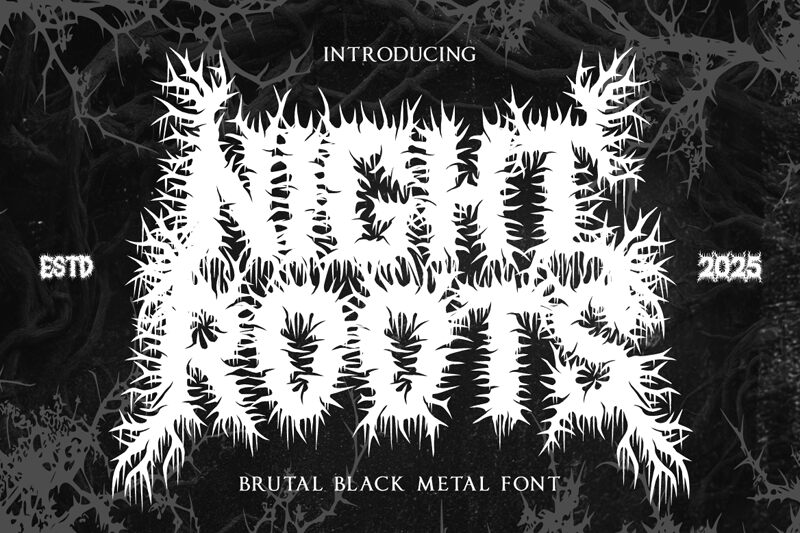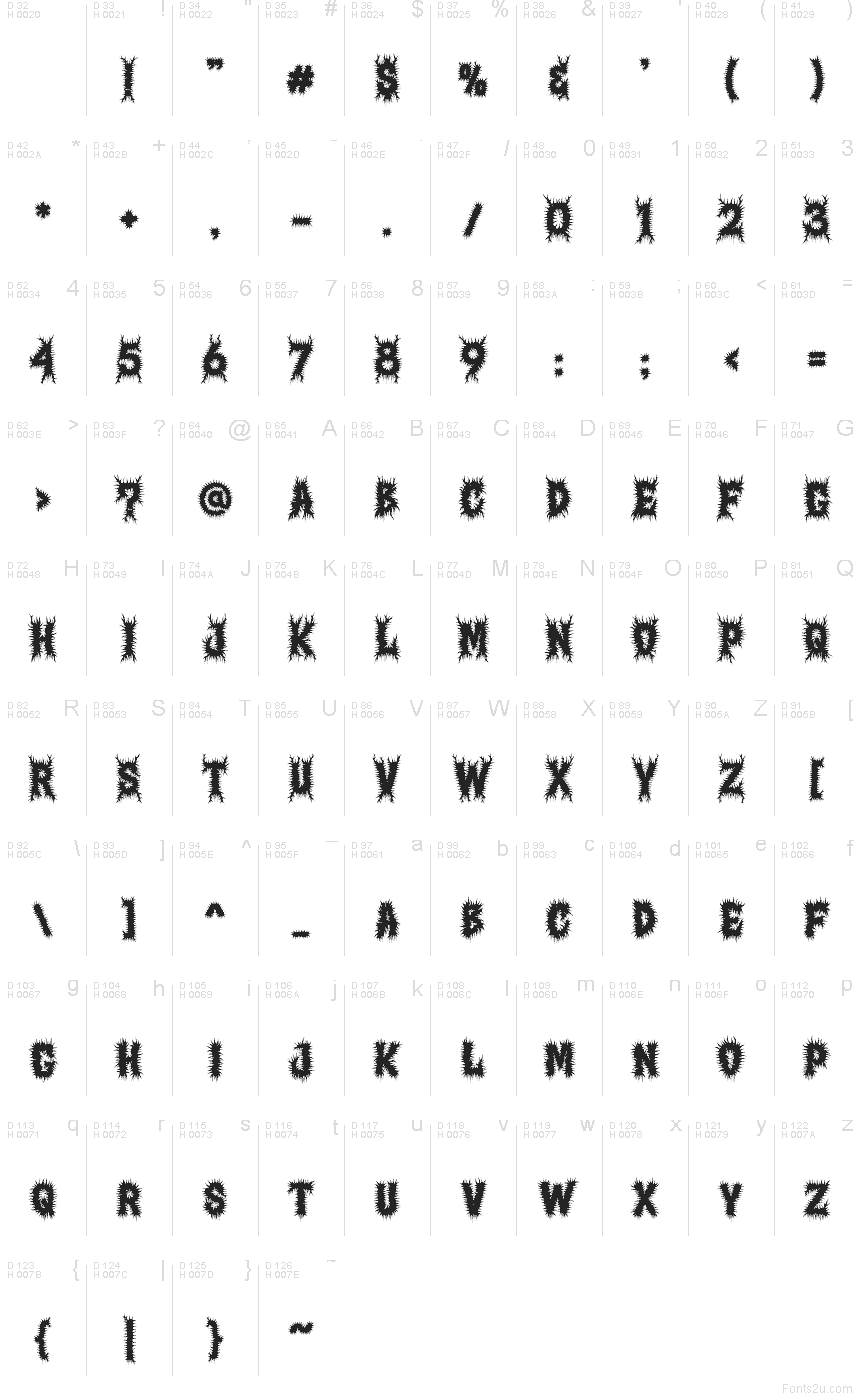
خط Night Roots من استوديو Shanaf هو خط عرض مجاني بنمط "Thorn-Gothic" (القوطي الشوكي) بلمسة قوطية عصرية. تبدو الحروف برية وغير مروضة، مليئة بالأشواك الحادة والامتدادات التي تشبه الجذور، مما يحول الأشكال السوداء الثقيلة إلى مزيج يجمع بين الخط القوطي (Blackletter) وتشابك الأشواك.
هذا الخط مثالي للملصقات، منشورات موسيقى الميتال، عناوين أفلام الرعب، أغلفة الألبومات، وتصاميم ملابس الشارع التي تتطلب طابعاً برياً بدلاً من التنسيق الأنيق. وبما أنه خط مجاني، فهو يعمل بشكل رائع للعناوين القصيرة، الشعارات (Wordmarks)، وعناوين البطاقات، حيث تضفي الصورة الظلية الكثيفة وزخارف الأشواك المتكررة على أي نص -حتى لو كان قصيراً- حضوراً غامضاً ومتشابكاً.